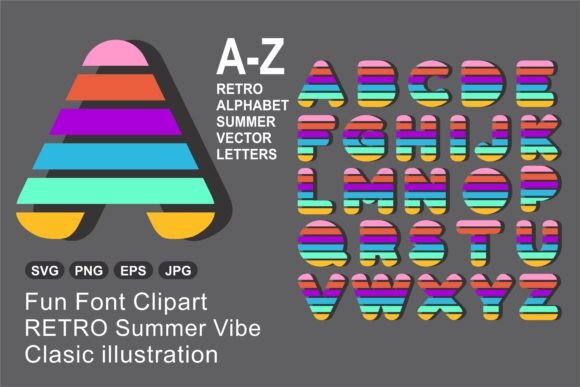
Retro Summer Font Alphabet a-Z
適切なデザイン要素を見つけるのは難しい場合がありますが、Retro Summer Font Alphabet a-Zは作品を即座に引き立てる優れたコレクションを提供します。
POD(オンデマンド印刷)製品、結婚式の招待状、またはソーシャルメディアのグラフィックを作成している場合でも、Retro Summer Font Alphabet a-Zは理想的です。